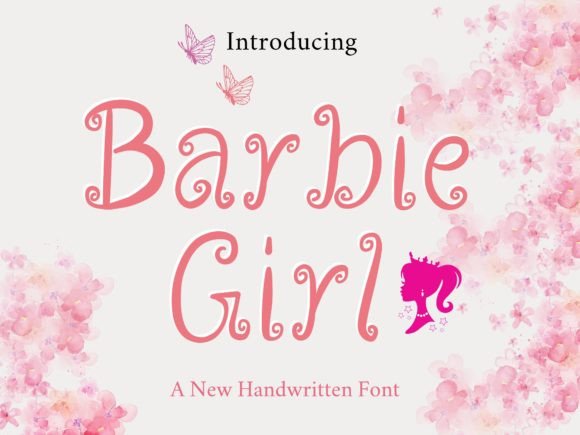
Barbie Girl
قد يكون العثور على عناصر التصميم المناسبة أمرًا صعبًا، ولكن Barbie Girl يقدم مجموعة استثنائية ترتقي بعملك على الفور.
تم تصميمه بدقة، ويوفر Barbie Girl متجهات نظيفة وطباعة سلسة وترخيصًا تجاريًا لراحة بالك.
سواء كنت تقوم بإنشاء منتجات الطباعة عند الطلب أو دعوات الزفاف أو رسومات وسائل التواصل الاجتماعي، فإن Barbie Girl هو الخيار المثالي.